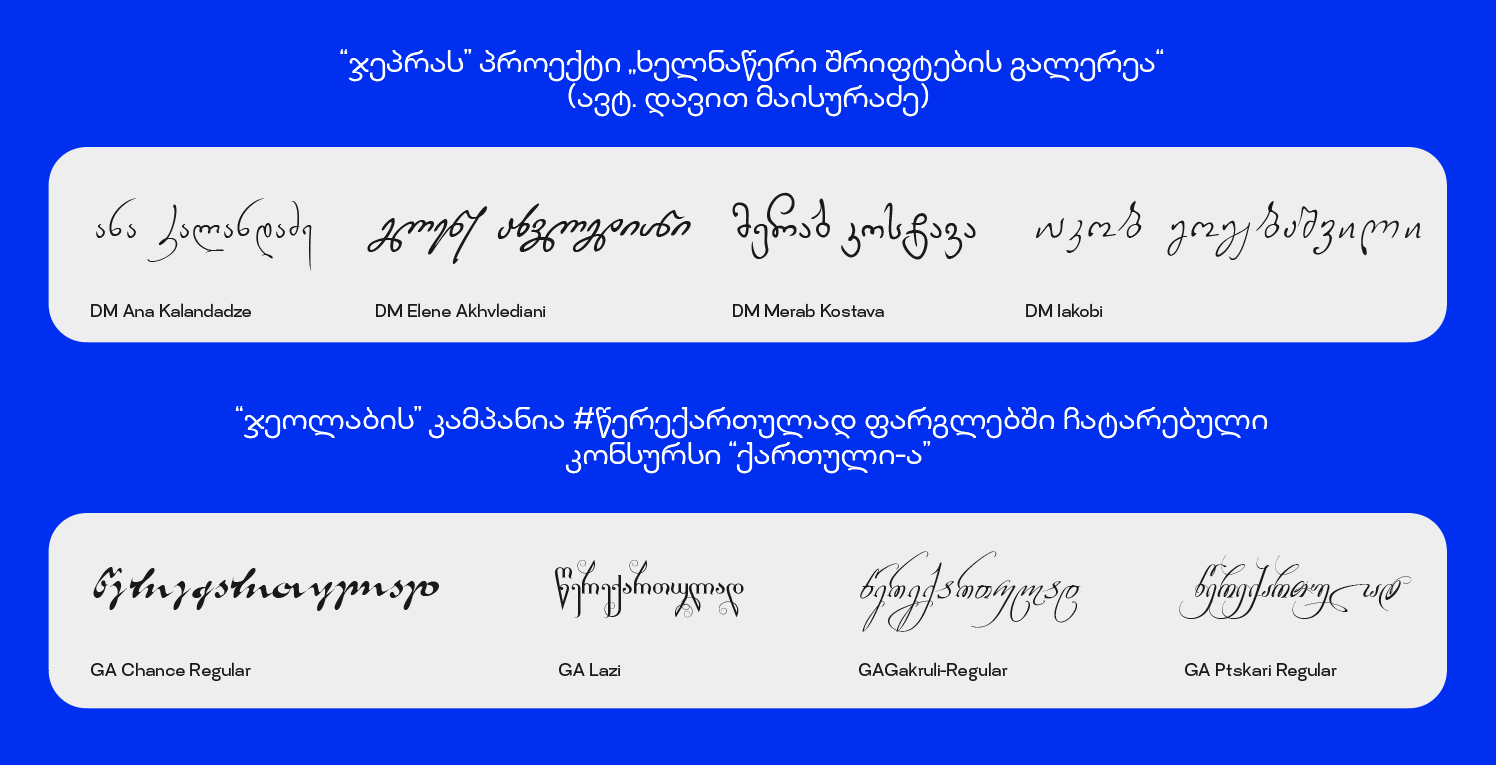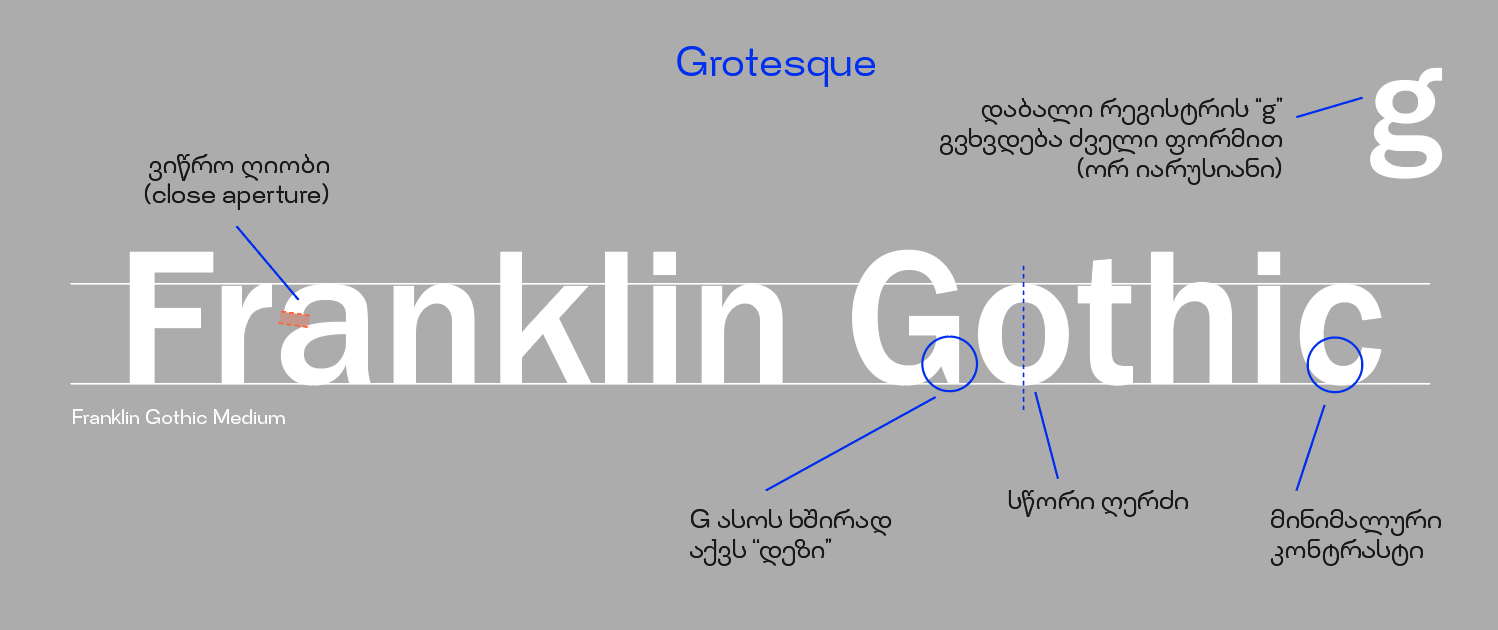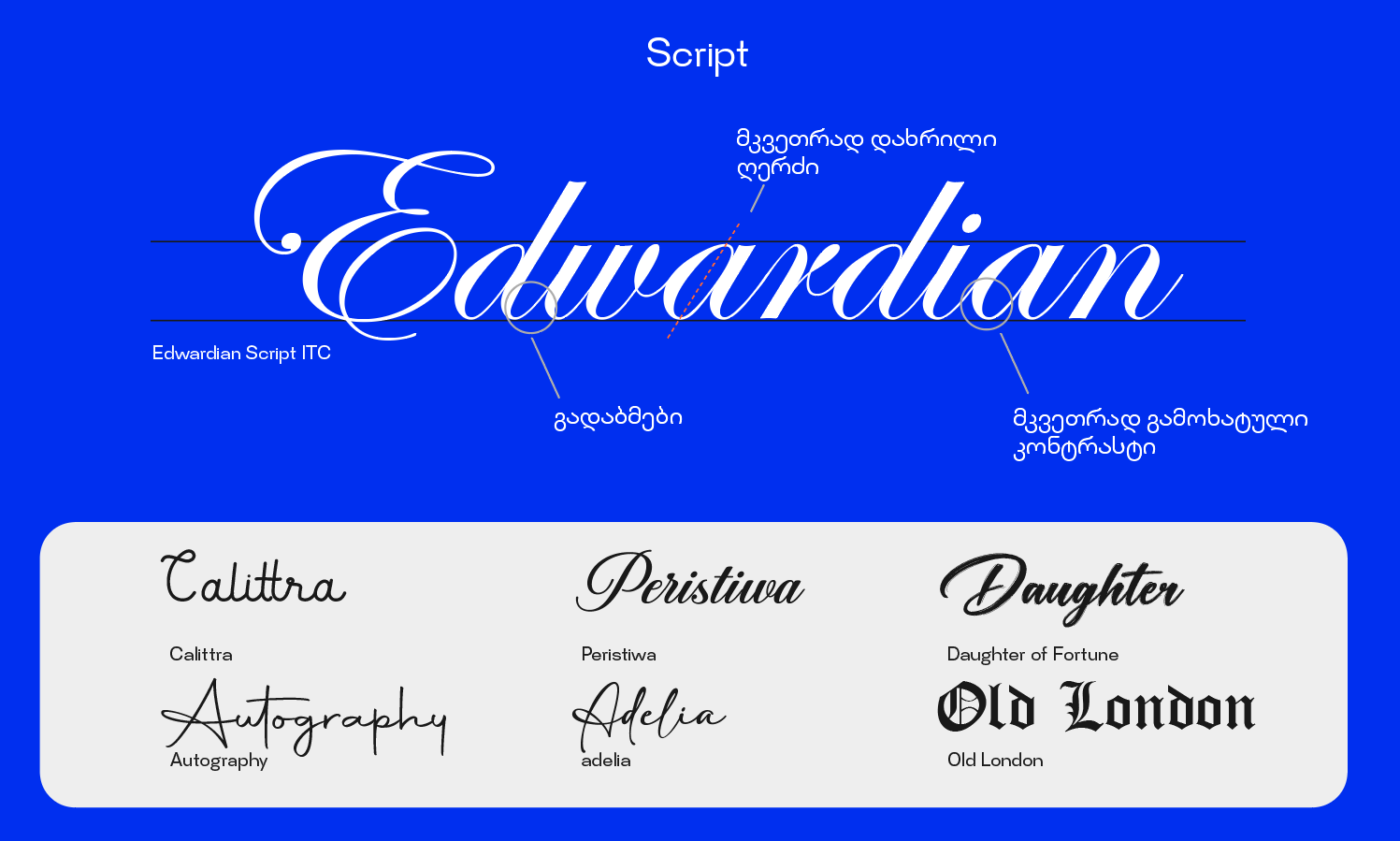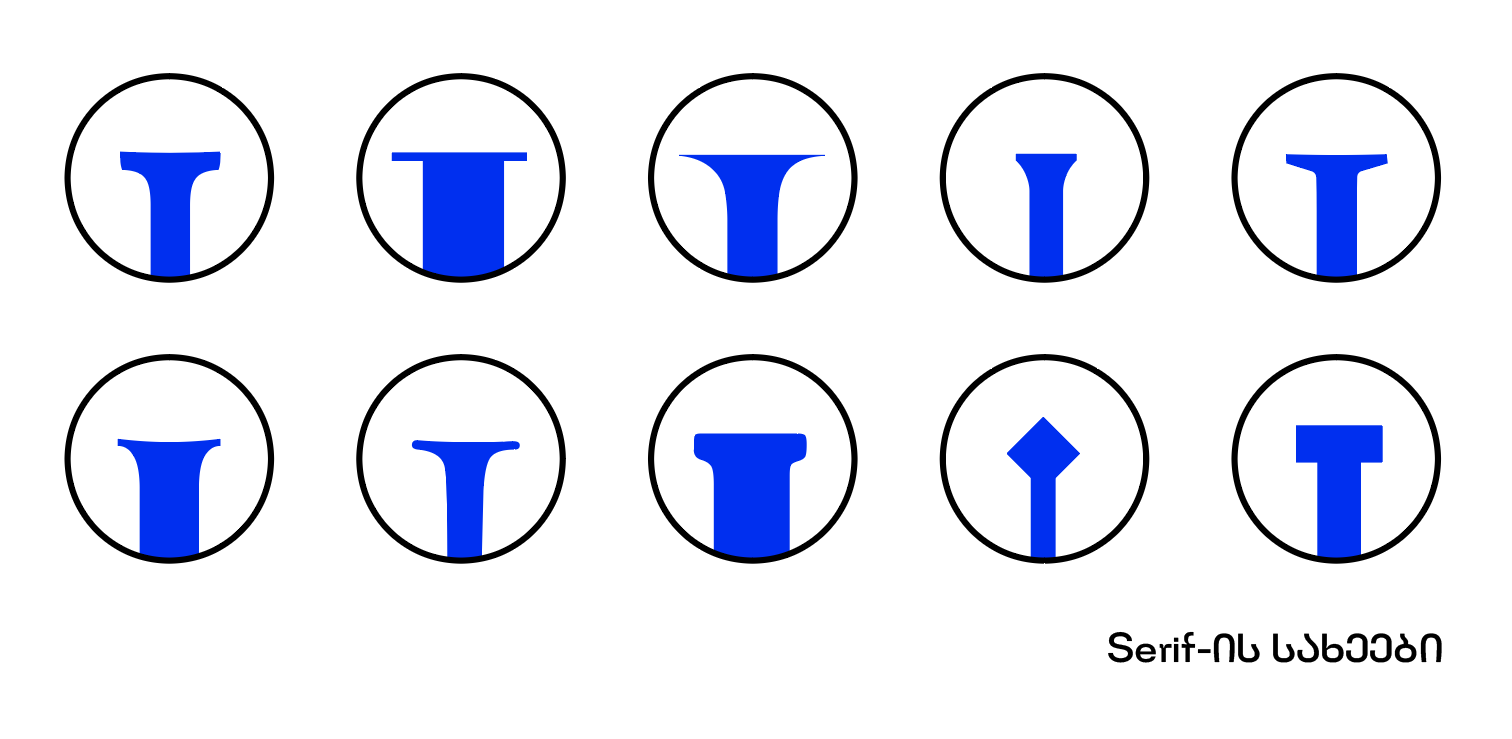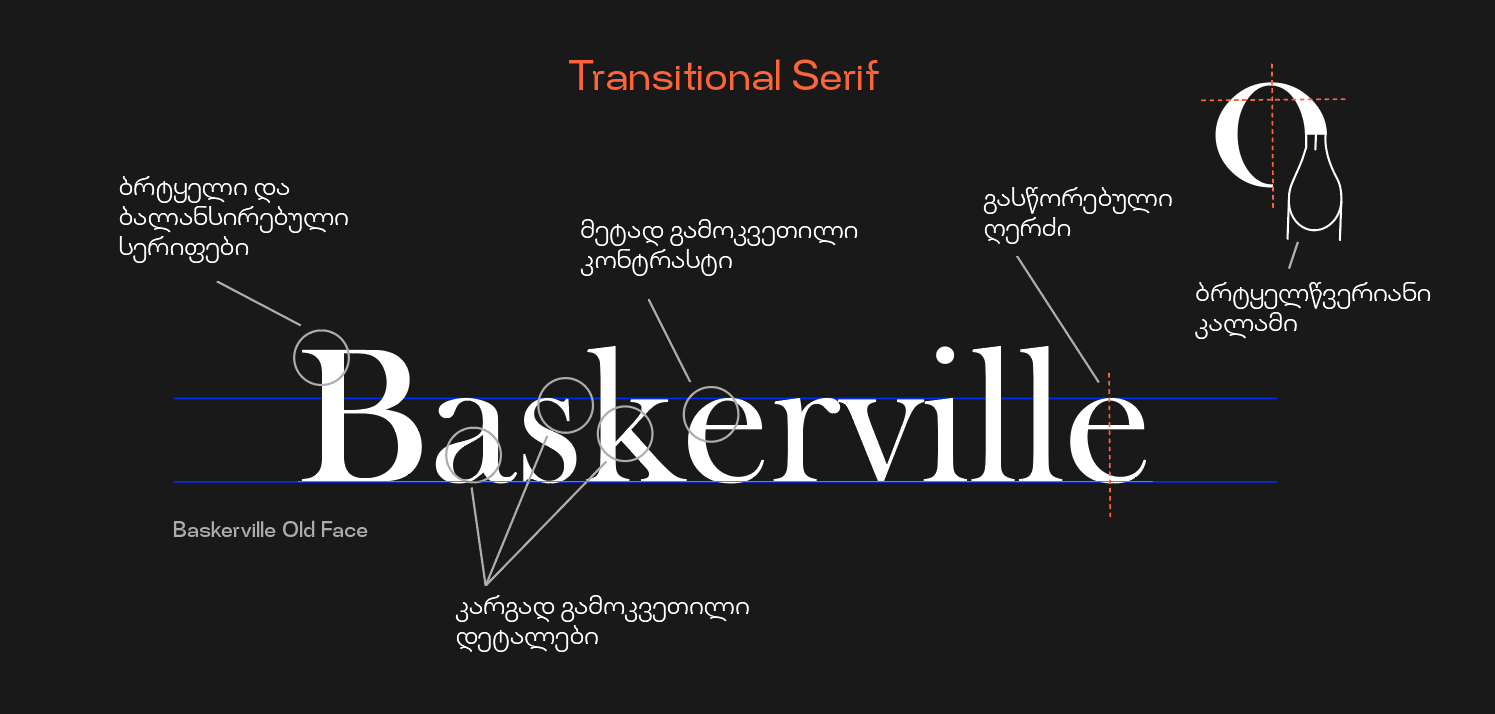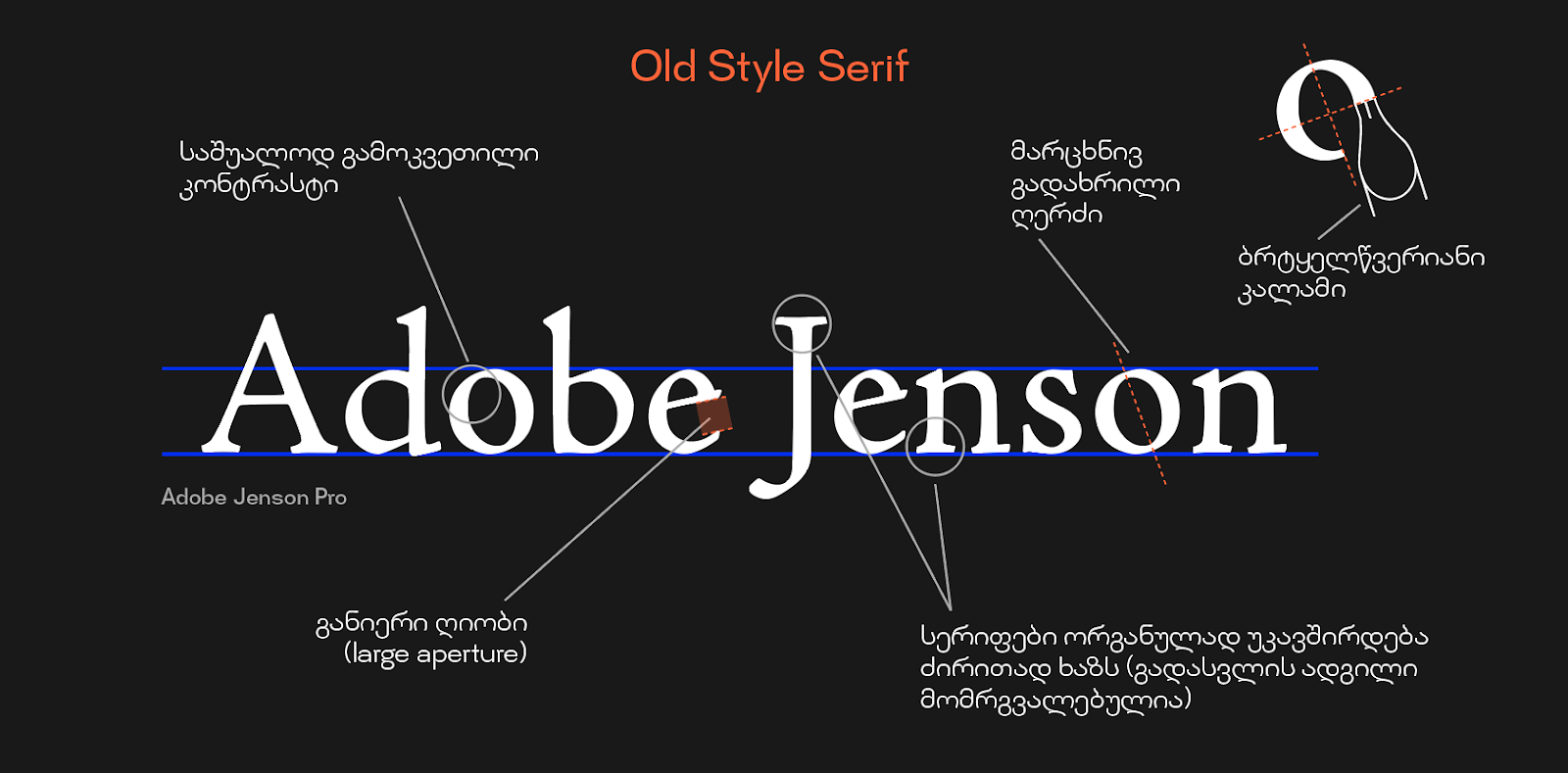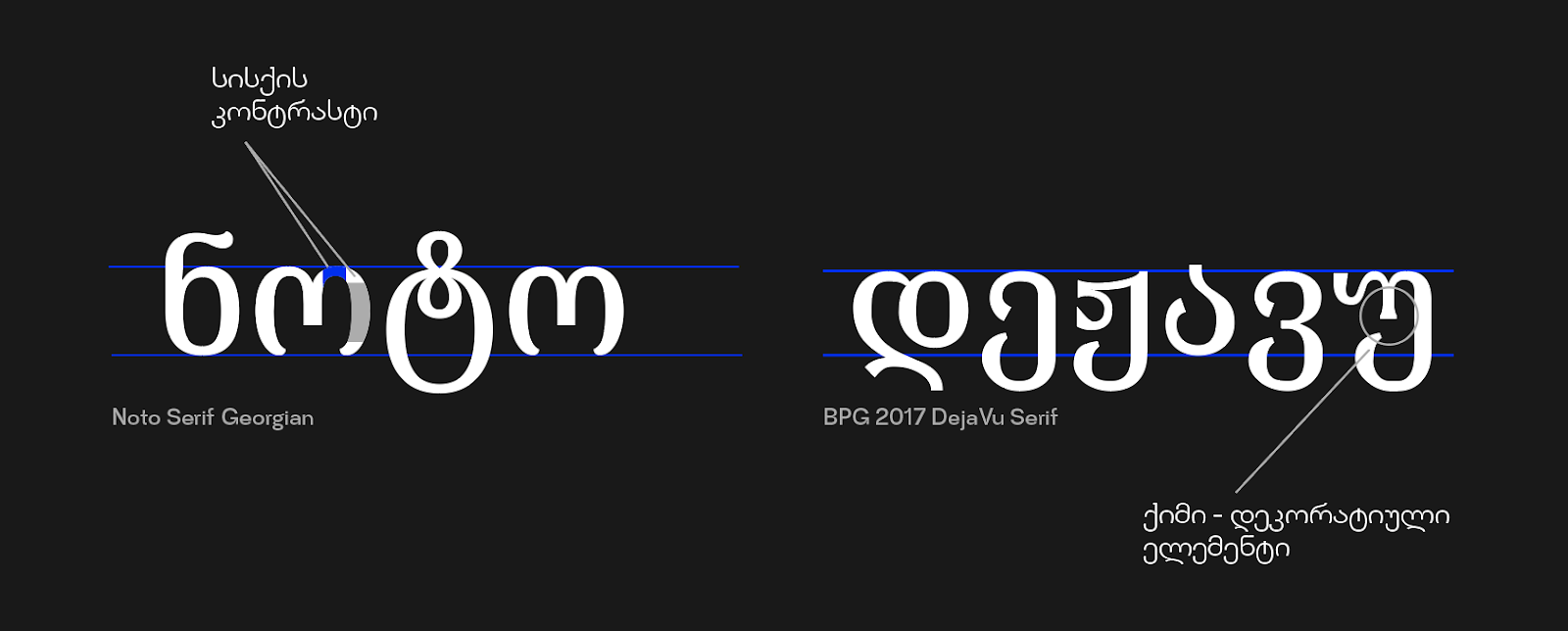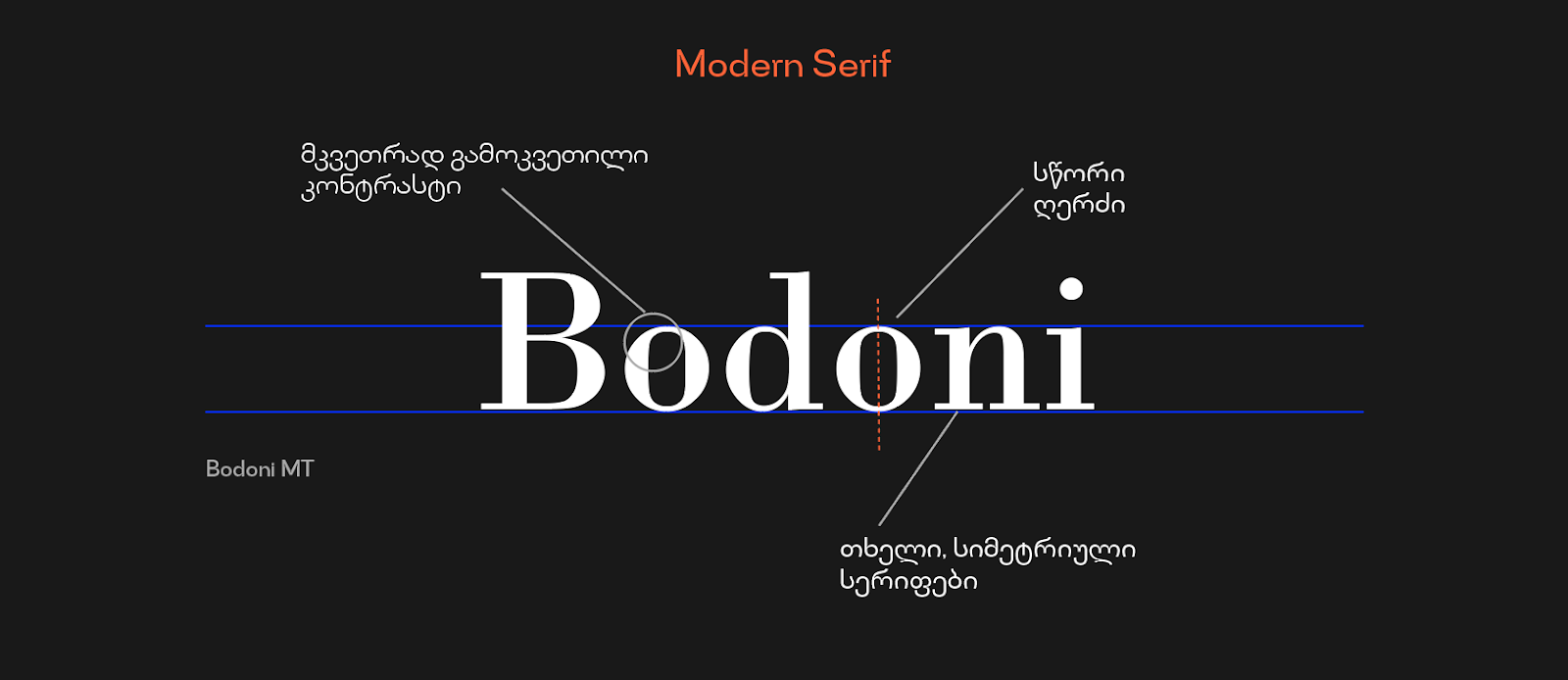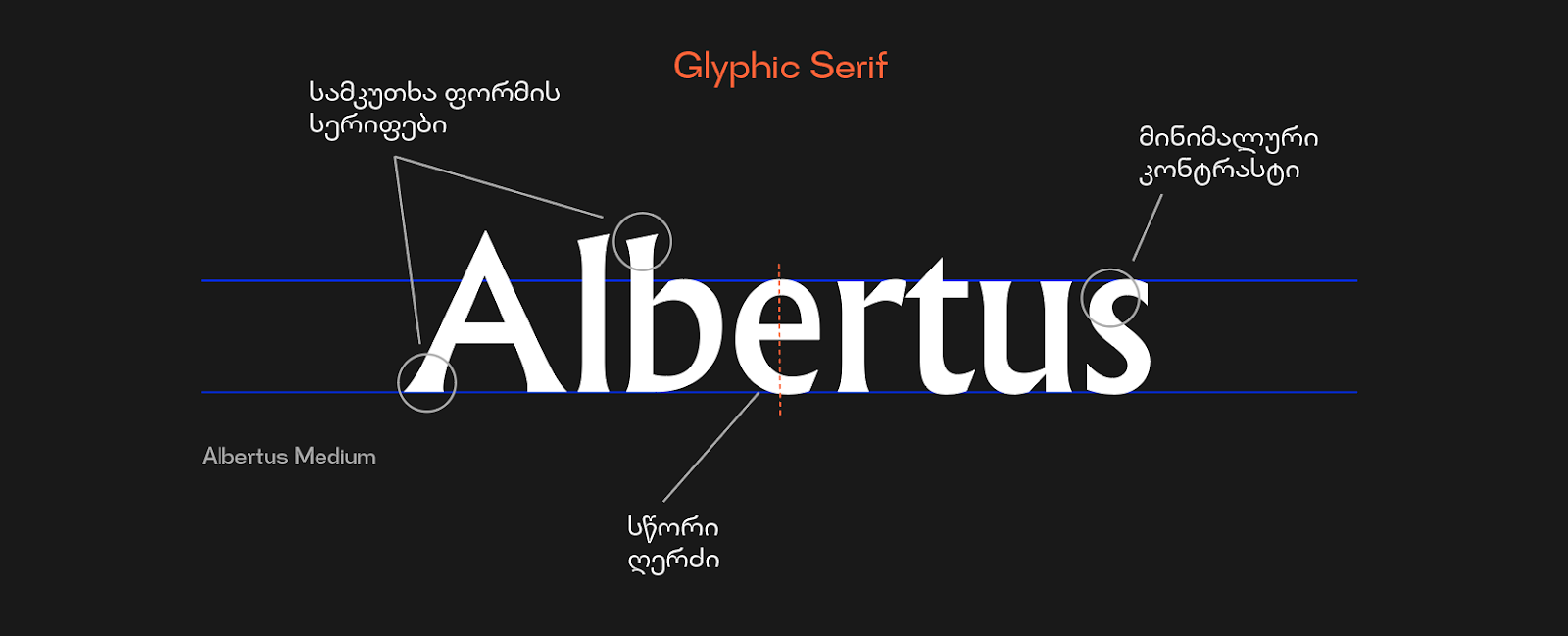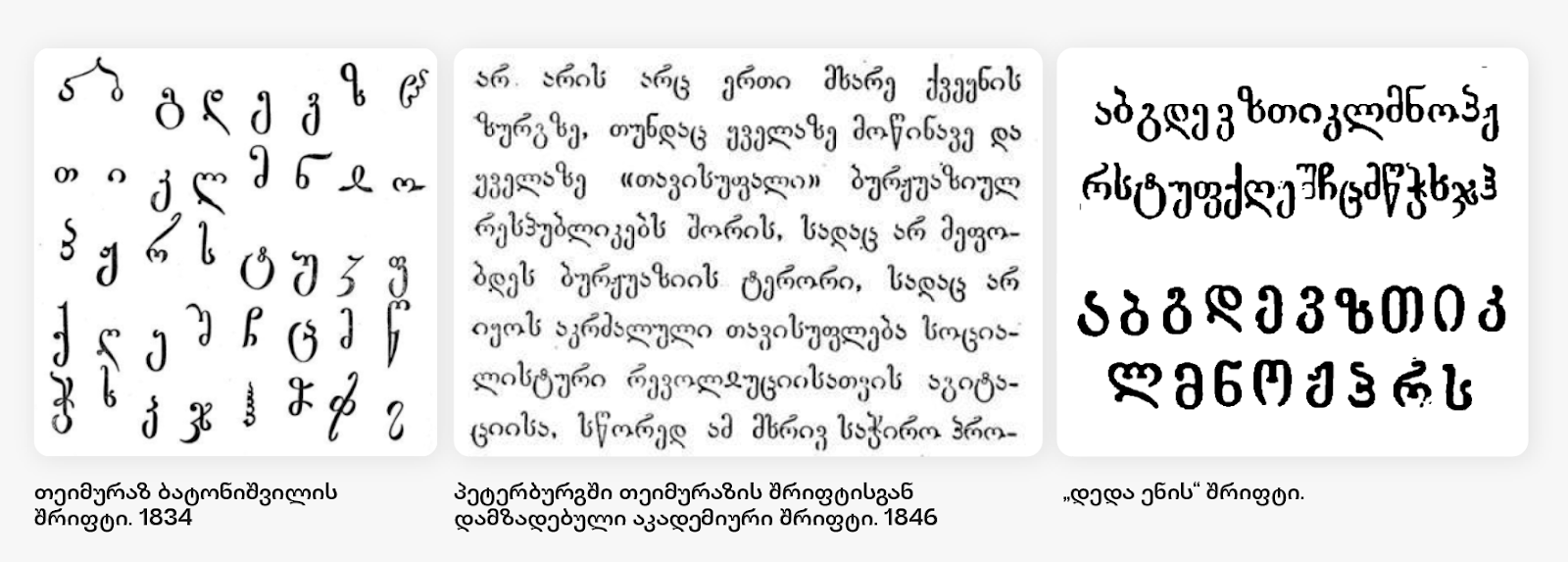
კითხვისას ჩვენ აღვიქვამთ არა მხოლოდ ტექსტის შინაარსს, ასევე მის ვიზუალურ სახესაც. სწორი შრიფტის არჩევა არც ისე მარტივი საქმეა დიზაინერისთვის. დღეისთვის არსებობს უამრავი განსხვავებული ვიზუალის შრიფტი. იმისათვის, რომ მათი მოძებნა და გამოყენება გამარტივდეს, შრიფტებს აერთიანებენ ჯგუფებად ვიზუალური ელემენტების მსგავსების მიხედვით. შრიფტების დაჯგუფება პირობითია. სტატიაში გაეცნობით ჩვენს შემოთავაზებულ ვარიანტს.
ᲡᲔᲠᲘᲤᲘ
Serif - სახელწოდება ნიშნავს „შვერილს“. ამ კატეგორიაში ერთიანდება შრიფტები, რომლებსაც დაბოლოებებზე გააჩნია პატარა შვერილები. ახასიათებთ კონტრასტი ვერტიკალური და ჰორიზონტალური ხაზების სისქეს შორის. შრიფტების ერთ-ერთი ყველაზე ძველი სახეობაა. დღეს ყველაზე ხშირად გამოიყენება ბეჭდურ პროდუქციაში.
Serif ჯგუფში გამოყოფენ რამოდენიმე ქვესახეობას:
ᲫᲕᲔᲚᲘ ᲡᲢᲘᲚᲘᲡ ᲡᲔᲠᲘᲤᲘ — Old Style Serif
ძველი სტილის შრიფტების ფორმა შემუშავებულია ხელნაწერებზე დაყრდნობით. ახასიათებთ ღერძის გადახრა და კონტრასტი, რაც დაკავშირებულია იმასთან, რომ ხელნაწერში ბრტყელწვერიანი კალმის გამოყენებისას იქმნებოდა ასოების ასეთი მოყვანილობა (იხ. სურათი). ასოების ღერძი მარცხნივაა გადახრილი, კონტრასტი საშუალოდაა გამოხატული, სერიფები ორგანულად უკავშირდება ძირითად ხაზებს.
მაგალითები: Jenson, Caslon, Garamond.
ᲒᲐᲠᲓᲐᲛᲐᲕᲐᲚᲘ ᲡᲔᲠᲘᲤᲘ — Transitional Serif
გარდამავალი სერიფის შრიფტების ფორმა შემუშავდა მე-18 საუკუნეში. წარმოადგენს შუალედურ ფორმას ძველ და თანამედროვე სერიფ შრიფტებს შორის და აქვს ორივე მათგანისთვის დამახასიათებებლი ფორმები.
კონტრასტი მეტადაა გამოხატული, ვიდრე ძველ სტილში. დახრილი ღერძი სწორდება და თითქმის ვერტიკალურ ფორმას იღებს. დეტალები მეტად გამოკვეთილია, სერიფები უფრო ბრტყელია.
მაგალითები: Baskerville, Times, Perpetua, Joanna.
ᲗᲐᲜᲐᲛᲔᲓᲠᲝᲕᲔ ᲡᲔᲠᲘᲤᲘ — Modern Serif
ამ სტილის ფუძემდებლები იყვნენ სასტამბო საქმის ცნობილი ოსტატები: დიდო (Firmin Didot) და ბოდონი (Giambattista Bodoni), რომლებმაც თავიანთი პროფესიონალიზმით შრიფტისა და სასტამბო დიზაინის სფერო მაღალ დონეზე აიყვანეს.
ძველი შრიფტებისგან განსხვავებით, რომლებიც ბრტყალწვერიანი კალმის მონასმების საფუძველზე შექმნა, თანამედროვე შრიფტების დიზაინზე გავლენა მოახდინა წვრილწვერიანმა კალამმა, რამაც განაპირობა ჰორიზონტალური ხაზის გამოხატული სიწვრილე.
ამ სტილისთვის დამახასიათებელია შტრიხის სისქეებს შორის მკვეთრად გამოხატული კონტრასტი.
მაგალითები: Bodoni, Didot, Aero, Ambroise.
ᲡᲚᲐᲑ ᲡᲔᲠᲘᲤᲘ — Slab Serif
ამ სტილს ზოგჯერ მოიხსენიებენ Mechanical ან Egyptian სახელით, რომელიც ძირითადად გამოიყენებოდა პლაკატების დიზაინში ყურადღების მისაქცევად. ამიტომ კარგად განასახიერებს მე-19 საუკუნის ინდუსტრიული რევოლუციის სულს, როცა აქტიურად დაიწყო დიდი ზომის სარეკლამო ბანერების და პლაკატების გამოყენება.
სლაბ სერიფ სტილისთვის დამახასიათებელია სქელი სწორხაზოვანი სერიფები. კონტრასტი სუსტადაა გამოხატული და ასოების შუატანის სიმაღლე საკმაოდ გაზრდილია. ასოების ფორმა კი ოთხკუთხედს უახლოვდება.
მაგალითები: Memphis, Rockwell, Clarendon, Sentinel.
ᲒᲚᲘᲤᲣᲠᲘ ᲡᲔᲠᲘᲤᲘ — Glyphic Serif
გლიფური შრიფტებს უფრო კვეთილი ფორმა ახასიათებთ. კონტრასტი, როგორც წესი, მინიმალურია, ღერძი - ვერტიკალური. დამახასიათებელი ნიშანია - სერიფების სამკუთხა ფორმა.
მაგალითები: Albertus, Cartier Book, Friz Quadrata.
ᲥᲐᲠᲗᲣᲚᲘ ᲡᲔᲠᲘᲤᲘ
ქართულში Serif კატეგორიის შრიფტებს არ აქვთ ამ ჯგუფის კლასიკური დამახასიათებელი დეტალი - ნაჭდევი. მათი მთავარი ვიზუალური ელემენტია - გამოხატული კონტრასტი ძირითად (მსხვილ) და ბეწვისებრ (წვრილ) ხაზს შორის. ასევე, ქართულ სერიფებში ხშირია დეკორატიული ელემენტების არსებობა.
ერთ-ერთი პირველი ქართული სერიფ კატეგორიის შრიფტი იყო აკადემიური, რომლისგანაც შემდეგ დამზადდა „დედაენის გარნიტური“.
მაგალითები: Noto Serif Georgian, BPG 2017 DejaVu Serif, Sylfaen.
ᲡᲐᲜᲡ ᲡᲔᲠᲘᲤᲘ — Sans Serif
ამ ჯგუფის სახელწოდება “სანს სერიფი” პირდაპირი თარგმნით ნიშნავს - „სერიფის გარეშე“. ამ ტიპის შრიფტების შექმნა დაიწყო მე-19-20 საუკუნეებში და იყო მარტივი, ორნამენტებისგან თავისუფალი შრიფტები. დღეს, ტექსტური შრიფტების უმეტესობა სწორედ ამ ჯგუფს მიეკუთვნება, რადგან მარტივი საკითხავია და თვალს ნაკლებად ღლის კითხვისას.
აქაც რამოდენიმე ძირითად ქვესახეობას გამოყოფენ:
ᲒᲠᲝᲢᲔᲡᲙᲘ — Grotesque
პირველი Sans Serif შრიფტები ცნობილი იყო, როგორც გროტესკი („მახინჯი“), რადგან ისტორიულ ელეგანტურ სტილებთან შედარებით ძალიან გამარტივებული და სადა იყო.
ადრეულ Sans Serif ჯგუფის შრიფტებში ჯერ კიდევ შენარჩუნებულია კლასიკური შრიფტების ელემენტები.
მაგალითები: Franklin Gothic
ᲜᲔᲝ-ᲒᲠᲝᲢᲔᲡᲙᲘ — Neo-Grotesque
ამ ჯგუფის შრიფტებში მთლიანად უარყოფილია შრიფტის ტრადიციული მახასიათებლები მარტივი და მინიმალისტური დიზაინის შესაქმნელად.
შტრიხებს შორის თითქმის არაა კონტრასტი, დაბოლოებები კი იდეალურადაა გასწორებული. სწორედ ამ სახეობას მიეკუთვნება მსოფლიოში ყველაზე ცნობილი შრიფტი - Helvetica.
მაგალითები: Helvetica, Univers.
ᲰᲣᲛᲐᲜᲘᲡᲢᲣᲠᲘ — Humanistic
ნეო გროტესკის ეპოქაში ტიპოგრაფთა ნაწილს სურდა შრიფტში „ადამიანური“ ხელწერის ზოგიერთი ელემენტის შენარჩუნება. ამიტომ შეიქმნა ჰუმანისტური სტილი.
მაგალითები: Gill Sans, Optima
ᲒᲔᲝᲛᲔᲢᲠᲘᲣᲚᲘ — Geometric
გეომეტრიული შრიფტები აგებულია მხოლოდ გეომეტრიული ფორმების გამოყენებით. ისინი ულტრათანამედროვედ ითვლება, თუმცა საკითხავად მოუხერხებელია.
მაგალითები: Futura, Avant Garde,
ᲥᲐᲠᲗᲣᲚᲘ ᲡᲐᲜᲡ ᲡᲔᲠᲘᲤᲘ
ქართულში Sans Serif სტილის შრიფტები იქმნებოდა ჯერ კიდევ სასტამბო შრიფტების პერიოდში. ამ ჯგუფის ქართულ შრიფტებს ასევე გააჩნია მარტივი, სადა და ადვილად საკითხავი მოხაზულობა. თავისუფალია ზედმეტი ორნამენტულობისგან.
მაგალითები: FiraGo, Noto sans Georgian, BPG Arial.
ᲙᲐᲚᲘᲒᲠᲐᲤᲘᲣᲚᲘ — Script
კალიგრაფიული და ხელნაწერი შრიფტების მიზანია ხელით დაწერილი ტექსტის შესახედაობის იმიტირება. სტილისტური დიაპაზონი საკმაოდ დიდი და მრავალფეროვანია. შეიძლება იყოს კლასიკური, ჰგავდეს კალიგრაფიული კალმით ნაწერის, ან უბრალო „ნაჯღაბნს“.
ამ კატეგორიის შრიფტებისთვის დამახასიათებელია ლიგატურები - გადაბმები, ასოების ღერძი უფრო ხშირად დახრილია. შრიფტის ფაილს, ძირითად სიმბოლოებთან ერთად, ხშირად ახლავს ასოების ალტერნატიული ვარიანტები - ტექსტისთვის უფრო ჰარმონიული შესახედაობის მისაცემად.
გამოიყენება სათაურებისა და მცირე ზომის ტექსტისთვის.
კალიგრაფიის ჯგუფშივე ერთიანდება გოტიკური სტილის შრიფტებიც, რომლებსაც დღეს ხშირად დეკორატიულ ჯგუფს მიაკუთვნებენ. პირველი ნაბეჭდი წიგნი - გუტენბერგის ბიბლია სწორედ გოტიკური შრიფტით დაიბეჭდა.
ქართულ შრიფტებს შორის, სხვადასხვა ფორმის კალიგრაფიული შრიფტები მოიპოვება. თუმცა კლასიკური კალიგრაფია, ლათინური შრიფტებისგან განსხვავებით, უმეტესად სწორი ღერძის მქონე ასოებს გულისხმობს, დამახასიათებელია გადაბმები. პირველი სასტამბო შრიფტები სწორედ ხელნაწერისგან იყო შექმნილი.
მაგალითები: Dm შრიფტები (DM Batonishvili, DM Ertoba, DM Evangelion, DM Themestia, ა.შ.), GA შრიფტები (GA Chance, GA Lazi, GA Gakruli, GA Ptskari, ა.შ.)
ᲛᲝᲜᲝᲒᲐᲜᲘᲕᲘ — Monospace
მონოგანივი შრიფტები. გულისხმობს იმას, რომ შრიფტის შემადგენელ ყველა ასოს აქვს ერთნაირი სიგანე.
პირველად მონოგანივი შრიფტები შეიქმნა საბეჭდი მანქანებისთვის. დღეისთვის კი უფრო ხშირად გამოიყენება პროგრამირების სფეროში კომპიუტერული კოდის ასაკრეფად, რადგან ასეთი შრიფტით აკრეფილ ტექსტში სიმბოლოები ერთმანეთის ქვეშაა მოქცეული და უფრო ადვილია შეცდომების გამოვლენა.
მაგალითები: Bitstram Vera Sans Mono, Geo Sabechdi Nusx ASTER
ᲓᲔᲙᲝᲠᲐᲢᲘᲣᲚᲘ — Decorative
დეკორატიული შრიფტების კატეგორია ყველაზე ფართო და მრავალფეროვანია. ამ კატეგორიაში ავტორები მეტ შემოქმედებით თავისუფლებას ავლენენ. ხშირად გამოიყენება ასოების არატრადიციული ფორმები და პროპორციები. დეკორატიული შრიფტები ვიზუალურად მიმზიდველი და საინტერესოა, დიზაინში მათი გამოყენება კი დაკვირვებას მოითხოვს.
მაგალითები: MetalLord, Saucer BB, GA Jubo, Geo Times Nusx, SS GEO CREEPSTER
ᲐᲠᲐᲐᲜᲑᲐᲜᲣᲠᲘ — Non Alphabet
არაანბანურ ფონტებში შედის ფონტები, რომლებიც არ მოიცავს ანბანურ სისტემას. შეიძლება განასახიერებდეს ნებისმიერ სიმბოლოების სეტს: აიქონებს, ვალუტის სიმბოლოებს, ორნამენტებს და ა.შ.
მაგალითები: Georgian Dactyl Font, IconBitOne, Segoe UI Emoji, Multimedia Icons